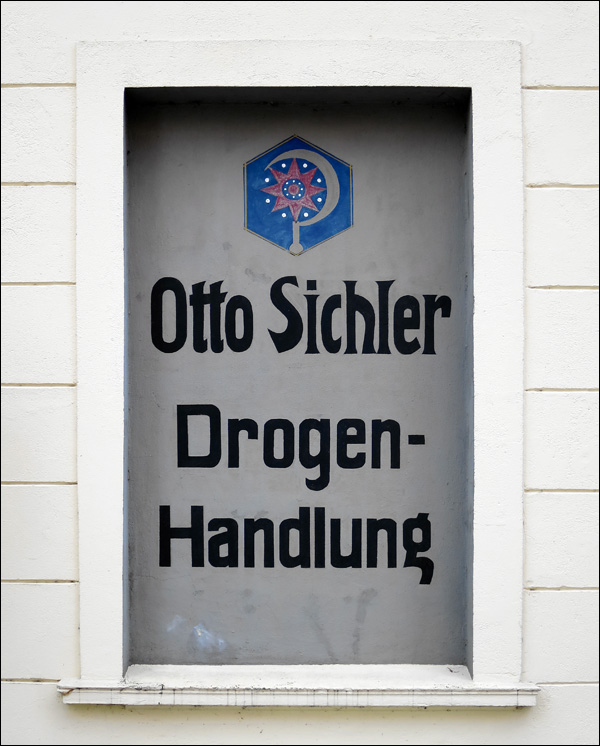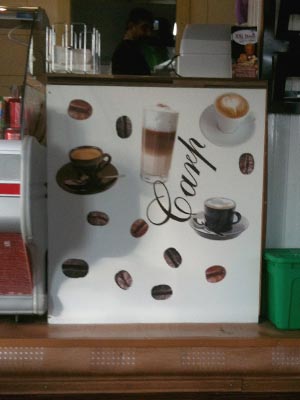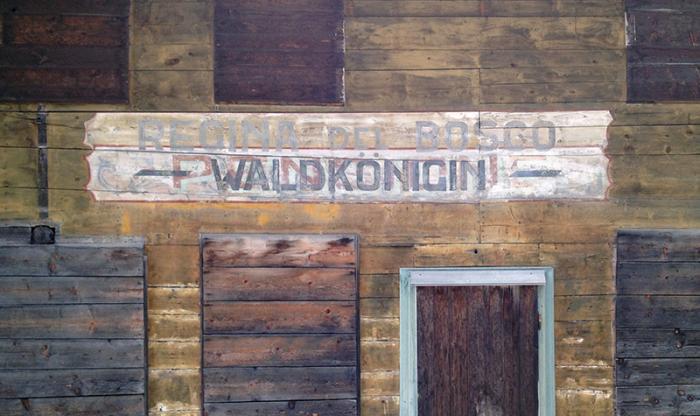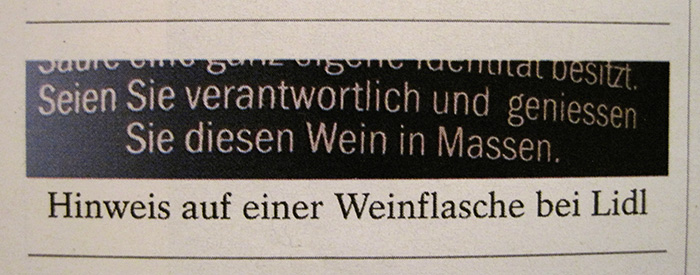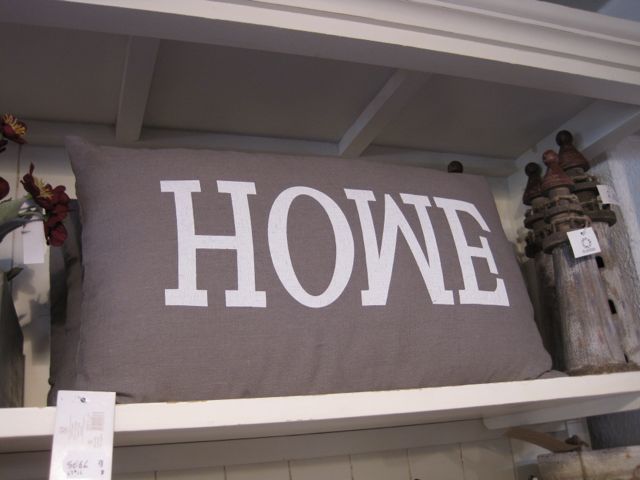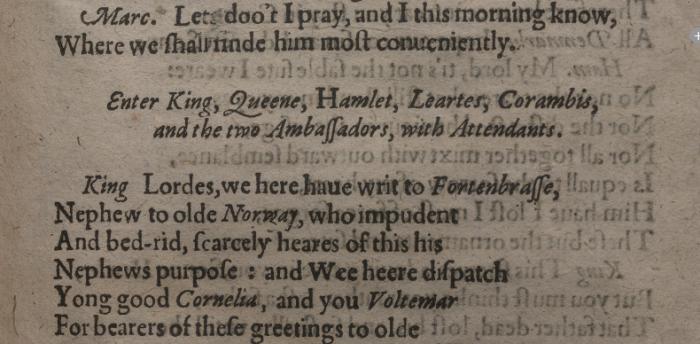
Gestern beim sonntäglichen Mal auf der Urlaubsheimreise entdeckt und ich konnte mir keinen Reim darauf machen, was da wohl mal stand, stehen sollte oder warum wer das überhaupt da hingeklebt hat!?
Blindtext im Sonderangebot...
Seit etwa 1974 besuchte ich einen meiner lieblings Elektronikläden an der Ecke Eppendorfer Chaussee/Falkenried. Mal, weil ich ein Bauteilk brauchte, das „hab ich nicht“ Balü mal wieder nicht hatte, mal, um einfach nach tollen Angeboten zu kramen, und mal, um ein Ersatzteil zu bekommen, das selbst der Hersteller nicht mehr liefern konnte - irgendwie wurde man immer fündig. Dann wurde erst renoviert - und plötzlich war der Laden leer.
Und dann war er wieder da, eitwa 100m weiter, und direkt Hohe Luft. Jetzt um einiges kleiner, mir nur noch dem Inhaber, aber durchaus an alte Traditionen anknüpfend. Ein Laden, aus dem man nicht unter veiner Stunde herumstöbern nicht raus kommt - und dann nicht ohne eine Tüte, oider gar einen ganzen PC aus Leasing-Rücklauf in der Hand...
Und so freute ich mich, dass man sich dort auch ins Internet begeben will - oder wollte? So richtig aus dem Knick kommt das Projekt wohl leider nicht. Schade eigentlich, dafür gibt es da wenigstens Blindtext satt im Sonderangebot:
Stimmt, manches ist da wirklich schon recht hübsch geworden, und das Logo, so wie den kleinen Roboter haben die schon seit den 70ern.
Und Phoibos: Ja, stimmt natürlich, aber das bring ich halt gern durcheinander. Hab das wahrscheinlich mit der Eimsbüttler Chaussee durcheiunander gewürfelt, wo HW-Elektronik angefangen hat, und dort, kurz vor dem Umzug nach Wandsbeck die längste Kunden-Schlange vor einem Computershop hatte, die ich je erlebt hatte.
Wenn der Platz nicht reicht, wird übereinander gemalt …
Einer meiner Profs – einer von denen mit eher mäßigem Tafelbild – berichtete mal von einem seiner Profs, der die Tafel zunächst mit weißer Kriede und anschließend mit gelber vollschrieb. Ohne zwischendrin zu wischen …
... und dann gibt es ja auch noch blaue Kreide und rote und grüne ...
Tafelwischen fand ich schon immer überflüssig  :gimmifive:
Ich habe mich aber tatsächlich schon mal gefreut, wenn nach einem halben Jahr in der neuen VHS-Saison meine alten Tafel-Kalligrafien noch da waren, weil ich beim letzten Termin meistens ein Beispiel für den nächsten Kurs ›angemalt‹ habe  :nicken:
Bin gerade hierüber ›gestolpert‹: http://www.quartos.org/index.html
Kann jemand was zu der Schrift sagen? England, 1603 – was hat man da für Schriften gedruckt?
Da behaupte noch einer, die Eszett-Fans würden solche Beispiele bloß künstlich konstruieren:
(Hohlspiegel dieser Woche)